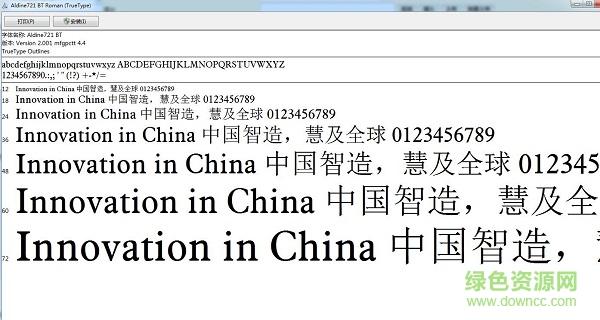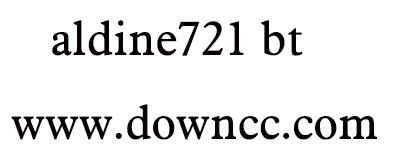
aldine721bt roman
aldine721 bt襯線字體匯聚了aldine721 bt roman常規(guī)體、aldine721 lt bt以及aldine721bt light等多款字體,可用于文章標(biāo)題、雜志排版等方面,有需要者千萬不要錯(cuò)過,趕緊下載收藏吧!
aldine721bt roman